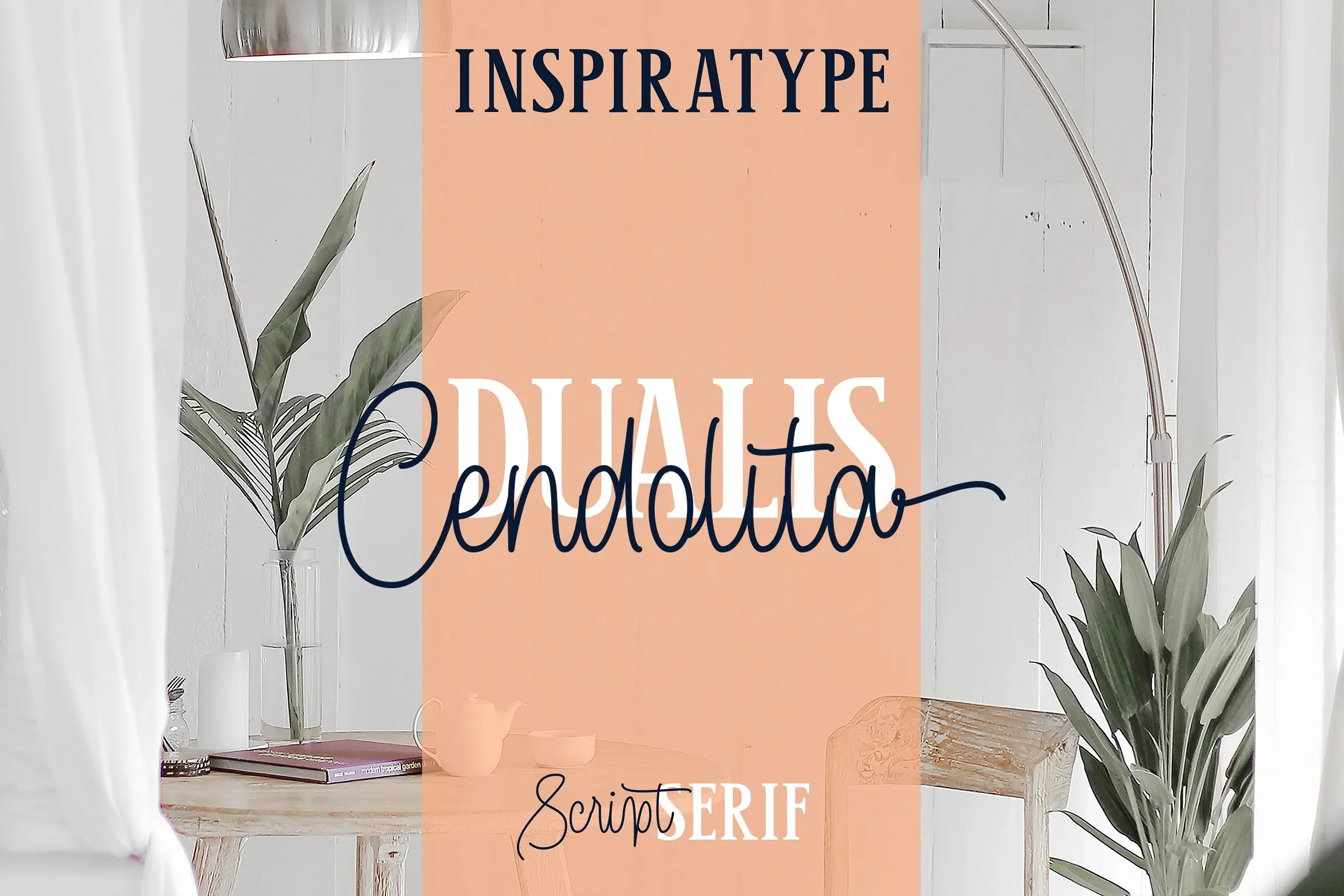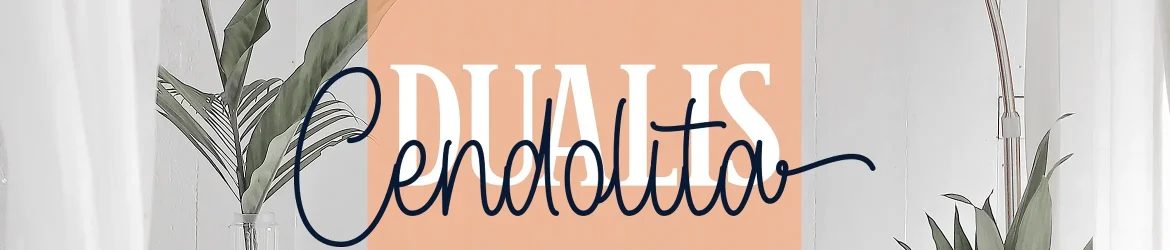
Cendolita Dualis Font Duo – Download Grátis
A Cendolita Dualis Font Duo é uma proposta singular para os designers brasileiros que desejam adicionar personalidade a seus projetos digitais. Desenvolvida pela Inspiratype, esta opção de script serif traz características únicas e inspiradoras em sua aparência, revolucionando o uso tradicional dos títulos e materiais gráficos. Com seu design feito à mão e inspirado nas antigas panfletagens clássicas, a Cendolita Dualis oferece um novo patamar de personalização. Ela vem com letras maiúsculas, minúsculas, números e sinais de pontuação, proporcionando uma amplidão de possibilidades para os designers. Este conjunto ainda inclui alternativas de opentype, ligaturas comuns e até mesmo swashes adicionais para que você possa personalizar as suas criações. Esta fonte é perfeita para uso em logotipos, carta de correspondência, panfletas, artefatos de roupas, etiquetas ou qualquer outra aplicação gráfica imaginada. Inspiratória e versátil, a Cendolita Dualis Font Duo atende as necessidades dos designers brasileiros que desejam dar um toque único em seus projetos digitais.